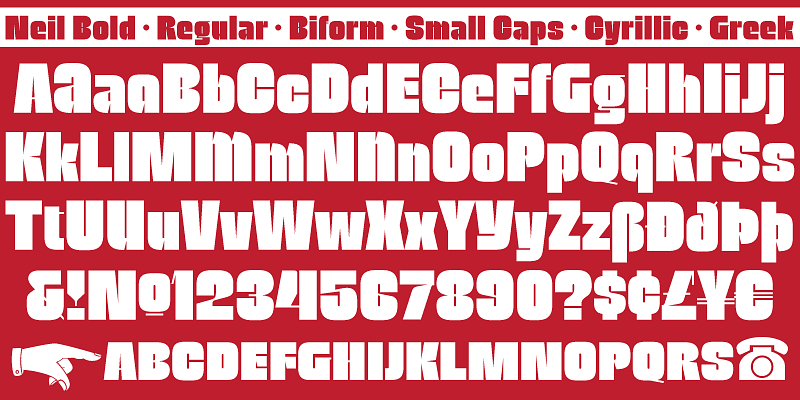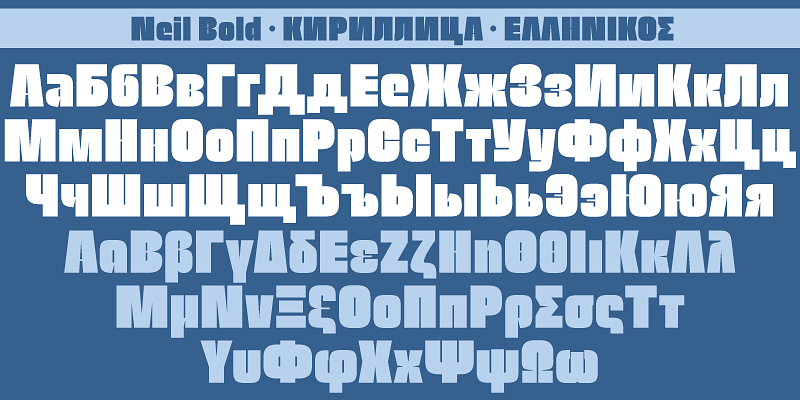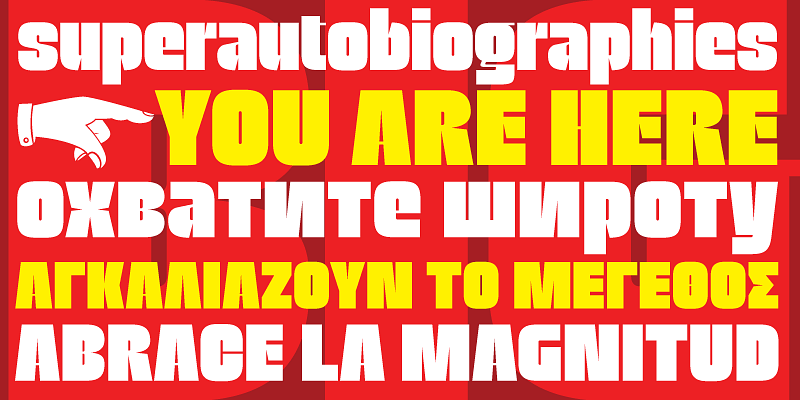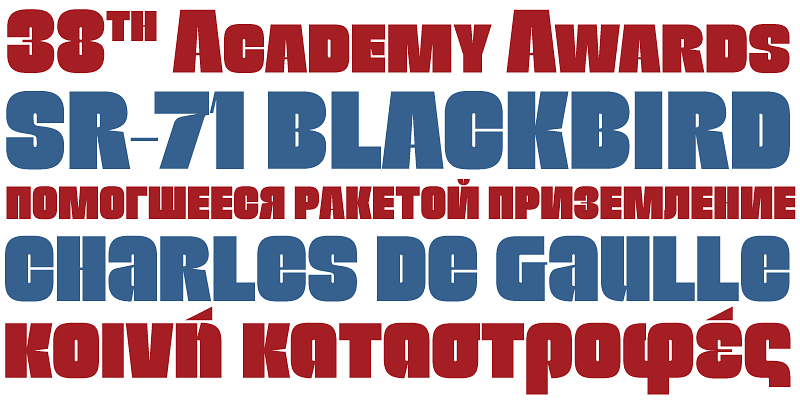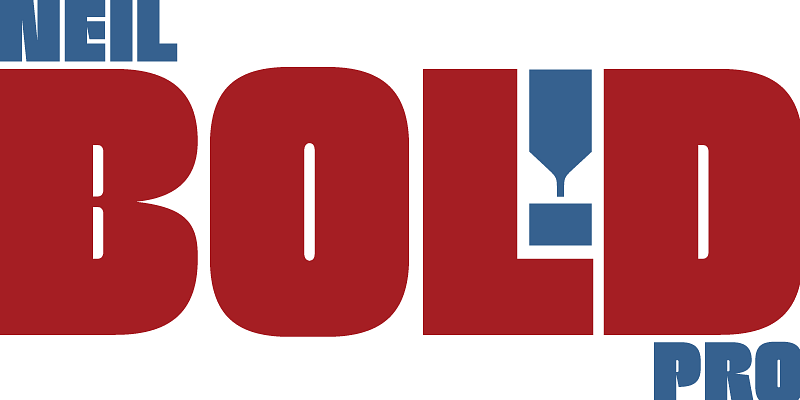
Neil Bold se publicó por primera vez en 1966 como un tipo de letra Typositor. Era el envoltorio de un disco de jazz favorito, especialmente en los discos de Blue Note y se usó bastante en portadas de libros de ciencia ficción durante el último tramo de la edad de oro del género.